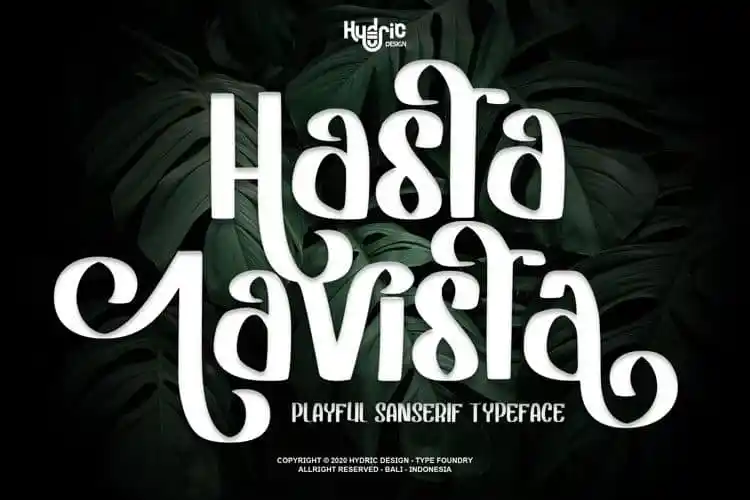
Hasta Lavista Display Font – Download Grátis
A Hasta Lavista Display Font é uma família única e divertida de serif que combina versatilidade com estilo elegante. Com 40+ ligaturas e mais de 100 alternativas, esta fonte oferece a habilidade de criar formas curvilíneas e shapes belas em apenas segundos. É perfeita para quem busca uma impressão gráfica divertida e personalizada sem sacrificar o aspecto elegante de um tipo serif. Com Hasta Lavista Display Font, você pode dar vida à sua arte digital e imprimir criatividade com um toque de leveza e elegância. Esta fonte é ideal tanto para aplicativos de design profissional quanto para trabalhos de arte pessoais. Junte-se a nós neste mundo onde cada caractere carrega o potencial de uma história, e Hasta Lavista Display Font está sempre à mão para dar vida ao seu trabalho.